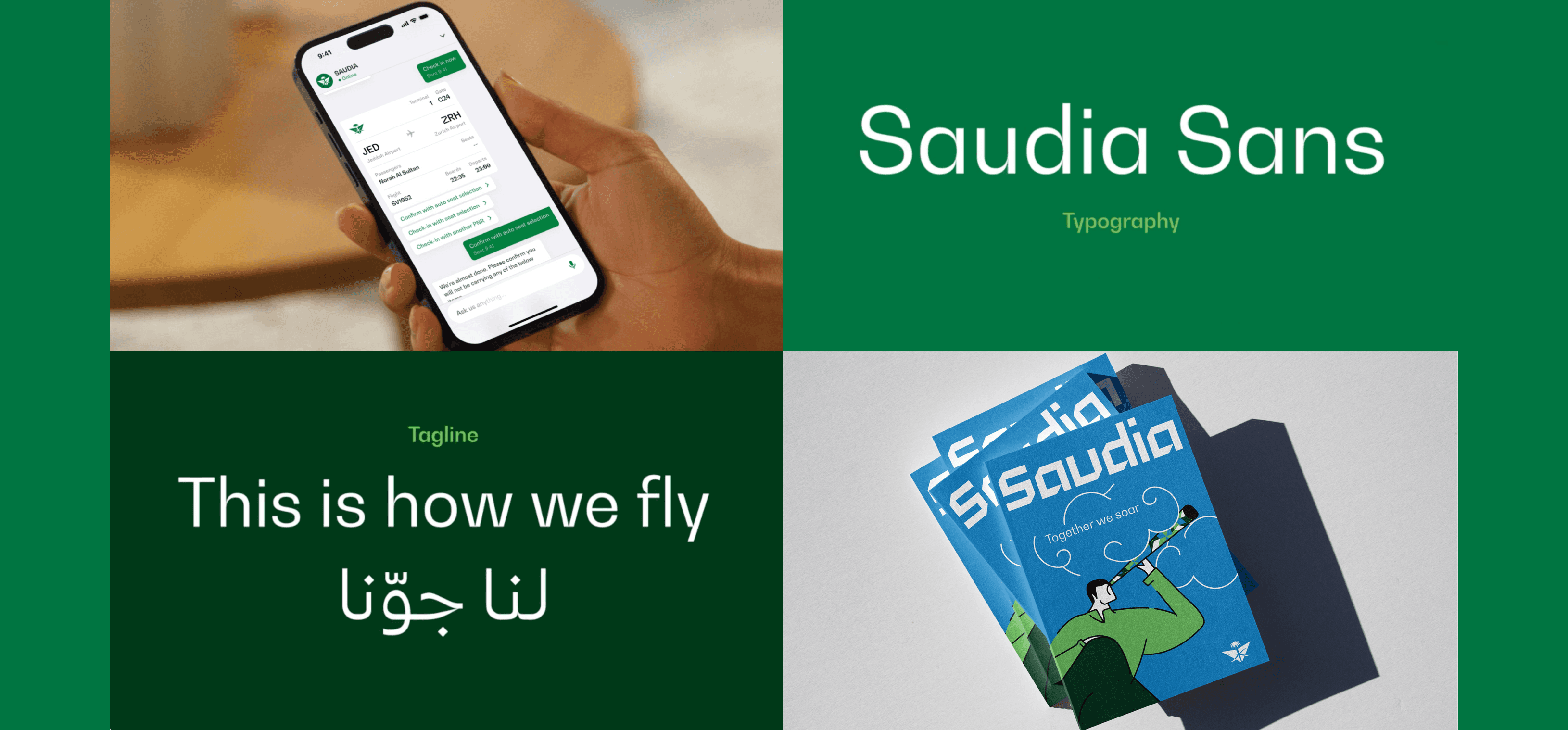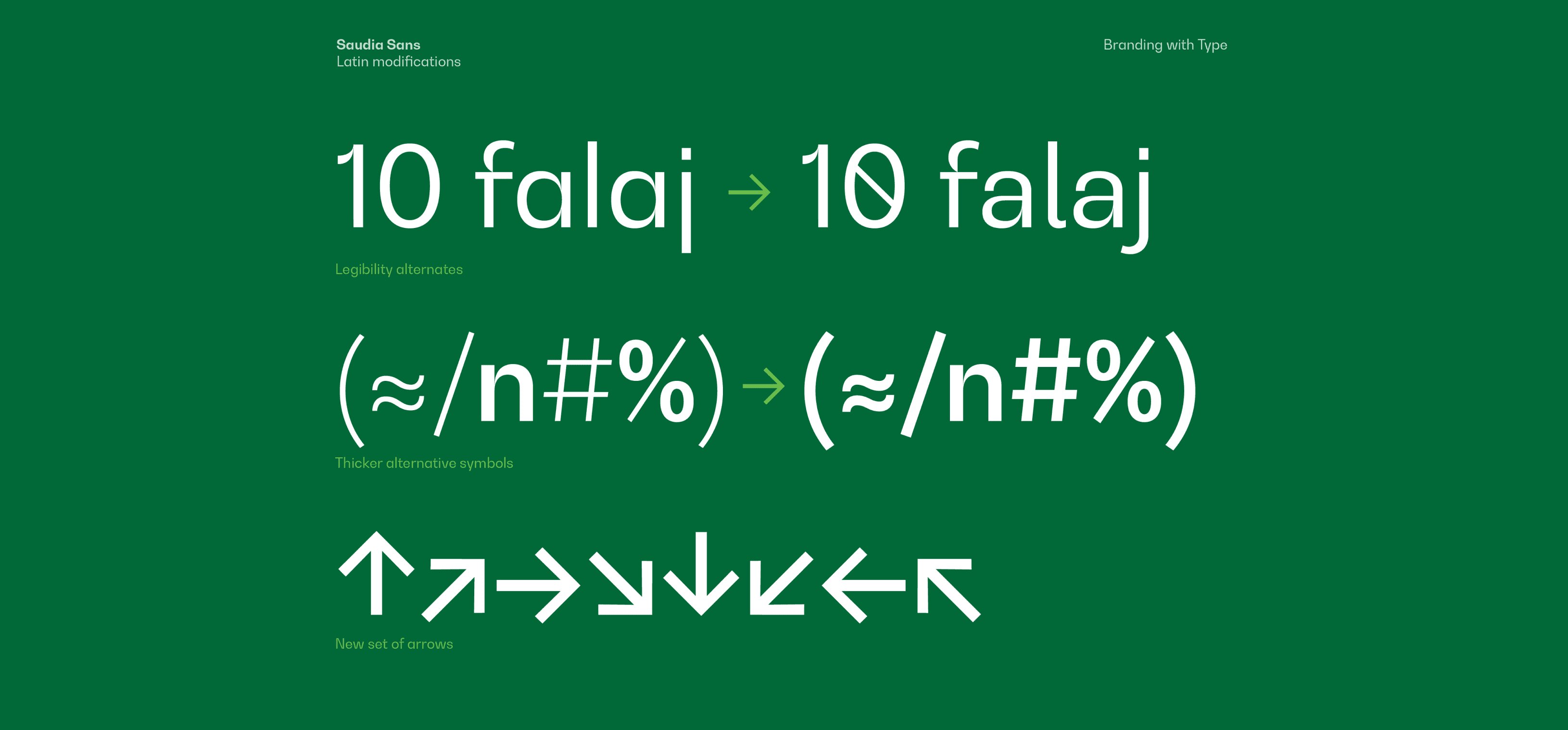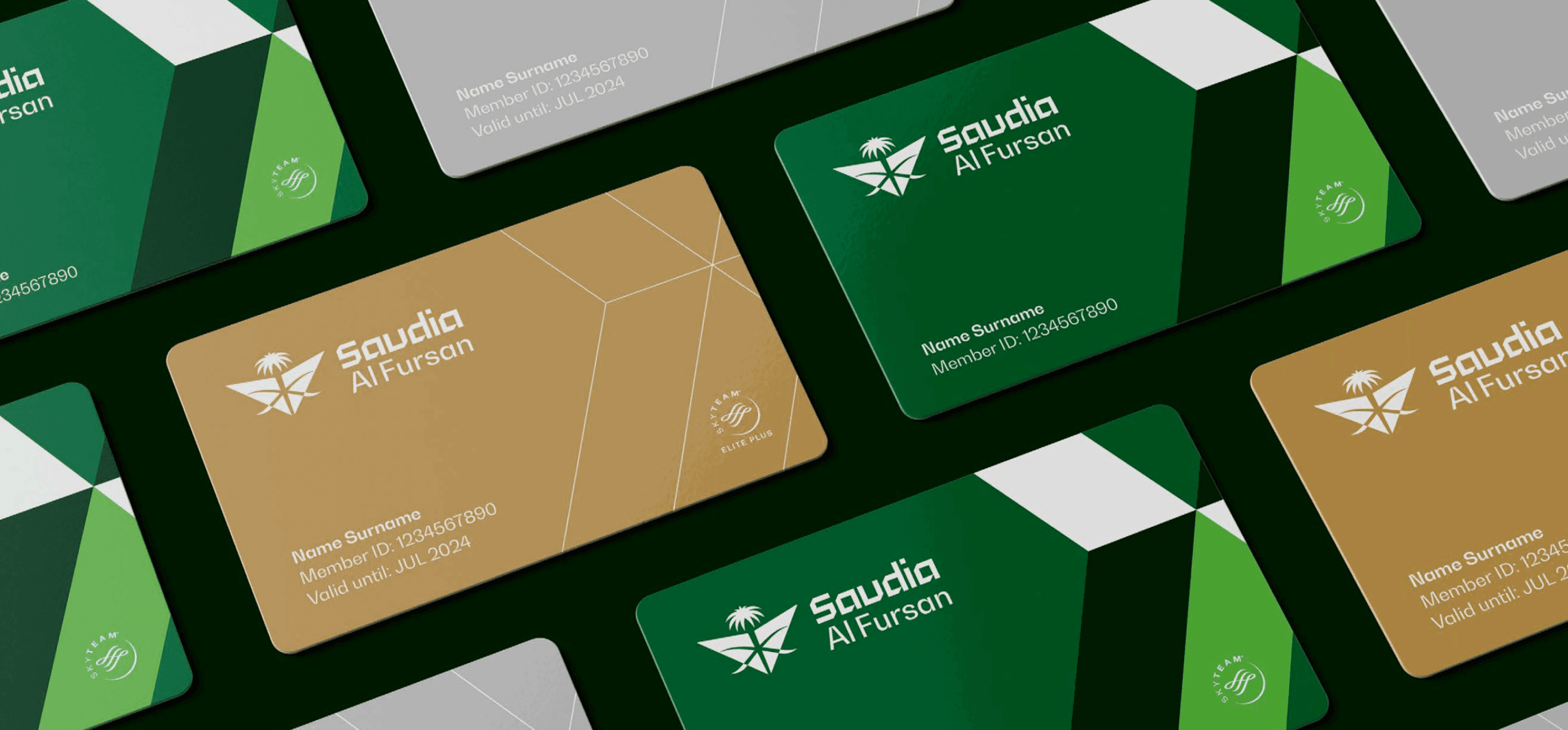
كانت فريق التصميم في شركة Landor قد اختار بالفعل خط Bw Gradual ليكون الخط المناسب للهوية البصرية الجديدة، لكن كان لا بد من إيجاد نظير عربي له.
كان التحدي الأكبر هو إيجاد التوازن الصحيح بين الوضوح البصري والاستمرارية الشكلية بين نظامي الكتابة، دون الإخلال بتجربة القارئ العربي.
فمن السهل الوقوع في فخ "تعريب الخط اللاتيني"، متجاهلين أن الخط العربي يتميّز بطابع خطيّ (كالليغرافي) عضوي أكثر بكثير من نظيره اللاتيني.
ولذلك، من الضروري الانتباه بدقة للفروقات الثقافية والعملية بين الأبجديتين.